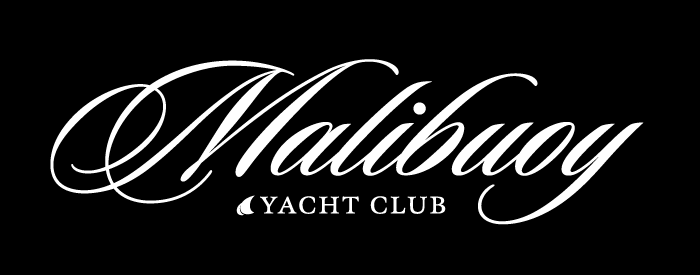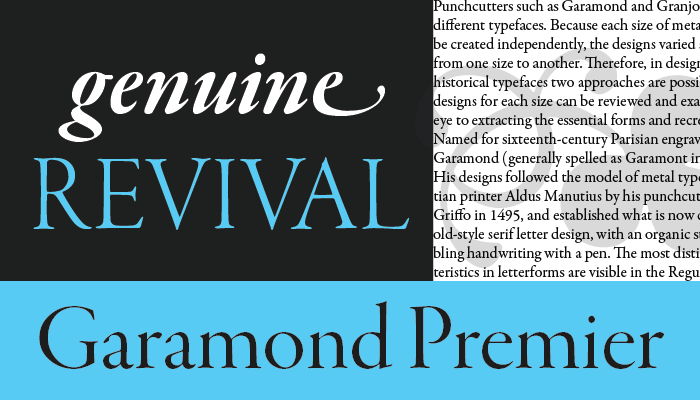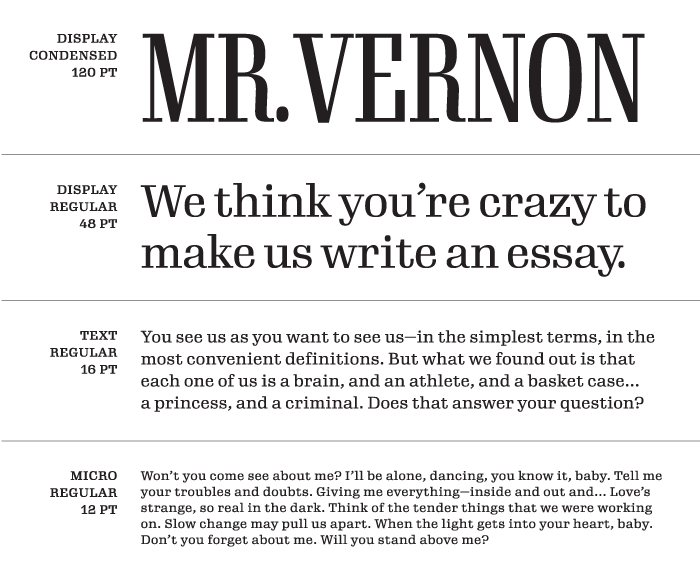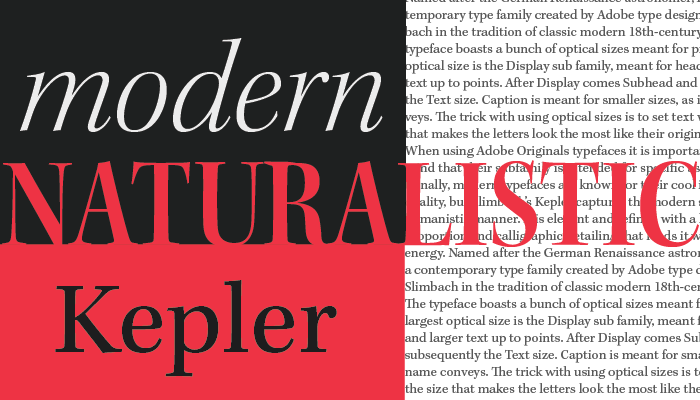
この1年で、私たちは過去最高となる7,000以上のフォントをライブラリに追加し、Creative Cloudの全プランのメンバーに提供されるフォントの総数は2倍の15,000以上となりました。私たちにとって大きな成果を残せた1年でしたが、このような継続的な成長は、世界中のタイプデザイナーおよびファウンダリー各社との意義深いパートナーシップがあってはじめて実現できるものです。
本日は、2つのフォント提供元について発表します。「Type Network」とアドビ社内のファウンダリー「Adobe Originals」、両者から供給された合計3,000を超えるフォントがデスクトップとWebでの利用で提供されるようになります。
Type Networkフォント
Type Networkは独立系タイプデザイナーのコレクティブで、2016年の設立以来ずっと私たちにとって嬉しいパートナーシップが続いています。本日のアップデートでは、私たちのライブラリに過去最大数のフォントを供給いただいた結果、2,500以上のType Networkフォントを、すべてのCreative Cloud有償メンバーが利用できるようになります。
Type Networkが供給するフォントは、Font BureauのBenton Sans、Giza、Bureau Grotのようなクラシックなものから、他のどれとも似ていないDJRのGimletのようなユニークでキャラの立ったものまで多岐にわたっています。今回の追加フォントには、筆記体のスペシャリストLipton Letter Designが手がけたSloop Scriptも含まれます。これを使うだけで手軽に文章に品格が備わる(このようなフォントの制作にはいかほどの手間がかけられたことか)フォントで、豊富な代替文字を使ったより装飾的な表現が可能です。
Adobe Originalsは、アドビ社内のタイプファウンダリーで、一部門として1980年代に設立されました。今回のフォント追加では、KeplerやGaramond Premier Proといったクラシックなフォントがデスクトップ用に提供されます。これらのフォントは単品販売あるいはWeb利用のみ(私たちのライブラリでも数種のウェイトしか提供していませんでした)で、利用のハードルが高いものでした。